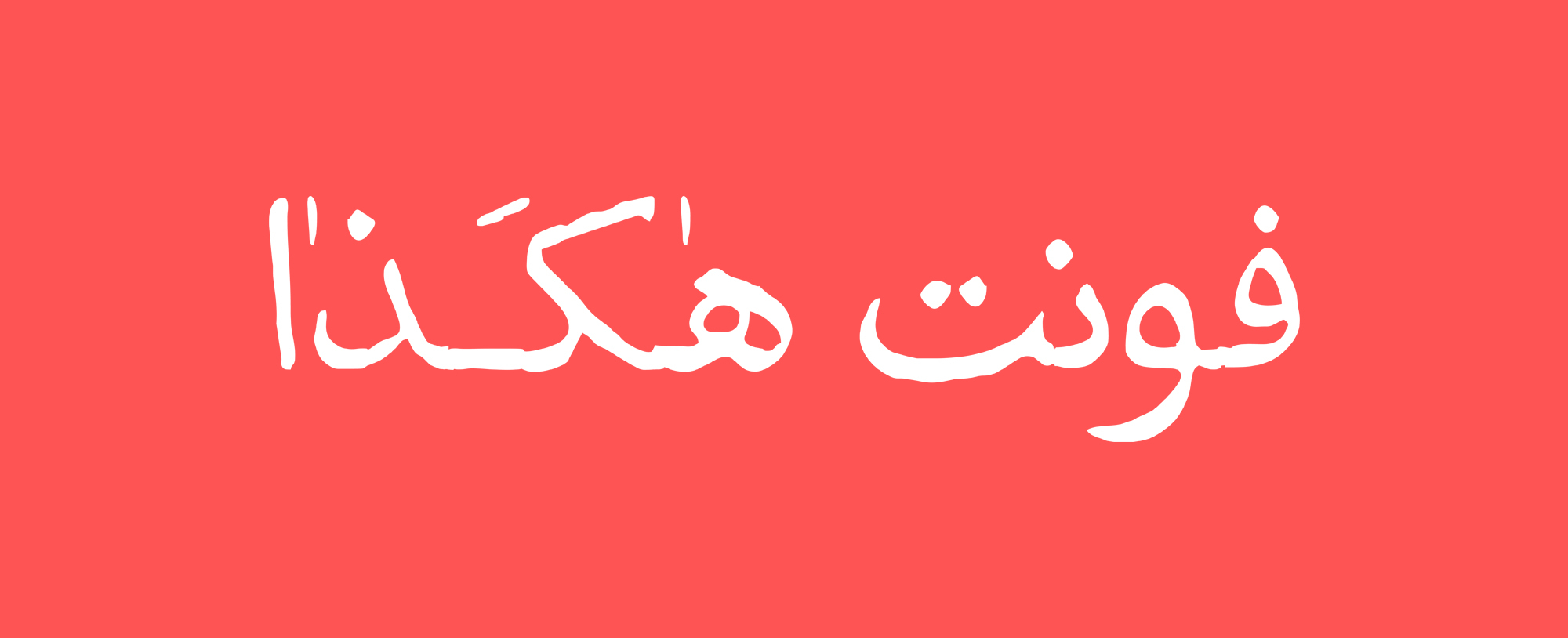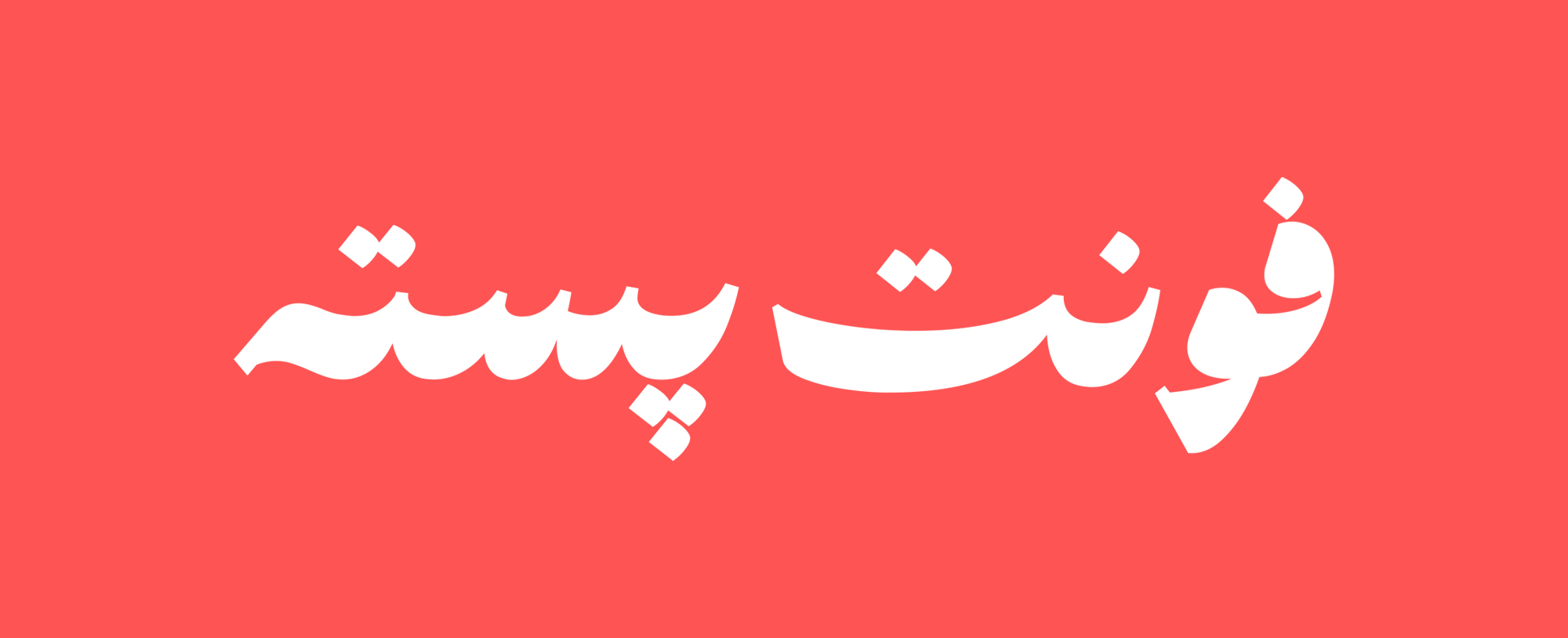
فونت پسته برداشتی شخصی و خلاق با نگاهی مدرن به خط نستعلیق است. فونت پسته تلاش میکند ترکیبی از زیبایی سنت و جذابیت نوآوری به طراحان و تایپوگرافرها ارائه کند. در پسته، هنر کلاسیک و سنتی با دیزاین مدرن تلاقی پیدا میکند. این فونت با استفاده از منحنیها و ضخامتهای متنوع و همچنین ترکیب زاویهها با فرمهای نرم و روان، جلوهای تازه و پویا به حروف میبخشد تا حس جریان را به مخاطب القا کند.
پسته روحیه جوان اما کلاسیک با چاشنی نمکی دارد، در عین حال که بی ادعاست اما جسور و مؤدب است و بدنبال خودنمایی نیست.
فونت پسته برای کسانی طراحی شده است که به دنبال زیبایی در کنار کاربرد هستند و میخواهند در طرحهای خود از تلفیق هنر قدیمی و مدرن بهره ببرند.
ایده طراحی فونتهای کاربردی با هدف استفاده از منابع غنی و ارزشمند خوشنویسی فارسی و نگاهی جدید به آنها در سال ۱۳۹۴ با طراحی فونت ایلیا آغاز شد. فونت پسته دومین پروژه به ثمر نشسته از این مجموعه طراحی فونتهای تجربی امیر مصباحی است.
روند دیزاین و تکامل پروژه فونت پسته همچنان ادامه خواهد داشت!
فونت شور با طراحی نرم و منحصر به فرد خود، تجربهای متفاوت از خواندن متنهای فارسی را ارائه میدهد. این فونت در دو استایل مختلف عرضه میشود: یکی با سرهای گرد و دیگری با سرهای تخت، که هر کدام از این استایلها در ۱۰ وزن موجود هستند.
فونت شور با انحناهای لطیف و طراحی انسانی خود، انتخابی عالی برای کسانی است که به دنبال یک فونت مدرن، کاربردی و زیبا برای پروژههای خود هستند. این فونت نه تنها در متون بلند و محیطهای دیجیتال عملکرد خوبی دارد، بلکه در طرحهای گرافیکی و تبلیغاتی نیز جلوهای ویژه ایجاد میکند.
فونت شور از نوع سنس است و یکی از اهداف اصلی طراحی فونت شور، دستیابی به خاکستری مناسب و کاربردی در محیطهای وب و اپلیکیشنهای فارسی بوده است. علاوه بر این، به طراحی جداگانه و خاص حروف نیز اهمیت زیادی داده شده است تا این فونت علاوه بر کاربردی بودن، زیبایی بصری قابل توجهی را نیز ارائه دهد.
فونت رادیو، یک فونت هندسی با رویکرد پیکسلی به حروف فارسی-عربی است. این فونت تداعی کنندهی گرافیک کامپیوترهای اولیه و کنسولهای بازی است. فونت رادیو با بدنه ای قطور و ساقههایی باریک، برای نوشتن عبارات مختصر و گرافیک خلاق پیشنهاد میشود. رادیو، دو سبک دارد و میتوانید از آن در طراحی پوستر، کاور و انواع تبلیغاتی استفاده کنید که میخواهید خاص و تکنولوژیک به نظر برسد.
فونت پارسا از دسته فونتهای دست نویس محسوب می شود. این فونت حاصل ۴سال بررسی، کار و رفع اشکال است. رسم الخط این فونت نزدیک به نستعلیق است و به شیوه این قلم تمامی حروف برای ی ، ه ، م ، ح ، ج، چ ، خ ، ر ، ز،ژ جداگانه طراحی شده است.
شخصیت اصلی فونت پارسا متاثر از نوع قلمی است که با آن نوشته شده. این قلم مانند قلمهای خوشنویسی دارای برشهای تیز نیست و تنوع ضخامت کمی دارد. همچنین به نسبت قلمهای تحریری (خودکاری) بولدتر است.
دیگر تفاوت فونت پارسا با فونتهای تحریری، نزول کمتر در حروف زیر خط کرسی است. که باعث میشود ترکیبات پراکندگی کمتری داشته باشد.
پیش از این نسخههای اولیهای از این فونت منتشر شده است که دارای مشکلاتی است و اعراب گذاری صحیح ندارد. این مشکلات در این نسخه از فونت پارسا رفع شده است.
فونت هاکذا با قدمتی از خاطره، رایحهای از مرکب چاپ، و توشهای از صنعت نشر ایران از دل سطربهسطر نشریات دههی پنجاه ایران استخراج و احیا شده است. اما این بازسازی، عینبهعین نبوده و اصلاحاتی در جزئیات آن ایجاد شده تا بهرهبرداری از فونت هاکذا را برای کاربرش آسانتر و بیدغدغهتر از نمونههای مشابه، و برای خوانندهاش لذتبخشتر از زمانهی خود کند.